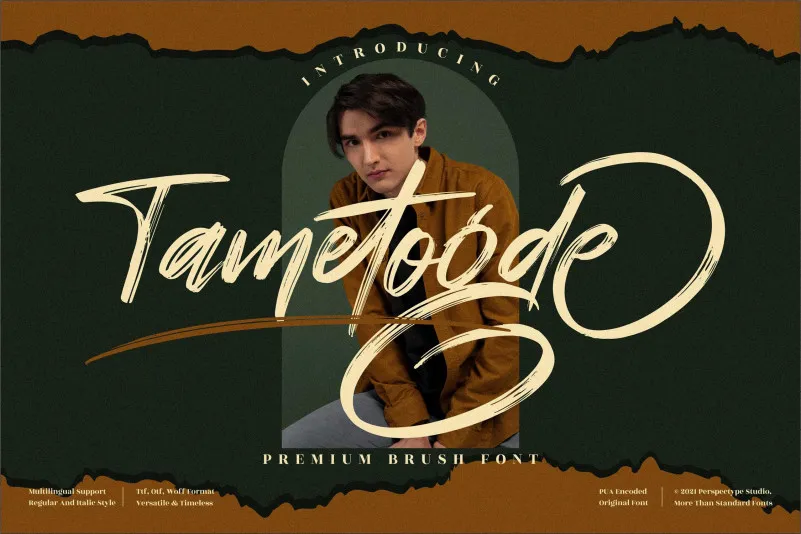
Tametogde Font – Download Grátis
Esta é uma fonte script cursiva e bold com traços bruscos. Perspectype criou-a meticulosamente para oferecer detalhes impressionantes. Seja qual seja o tópico, essa fonte será um excelente recurso para sua biblioteca de fontes, pois pode melhorar qualquer criação. O fato de ser PUA-encoded significa que você terá acesso fácil a todos os símbolos e swashes.